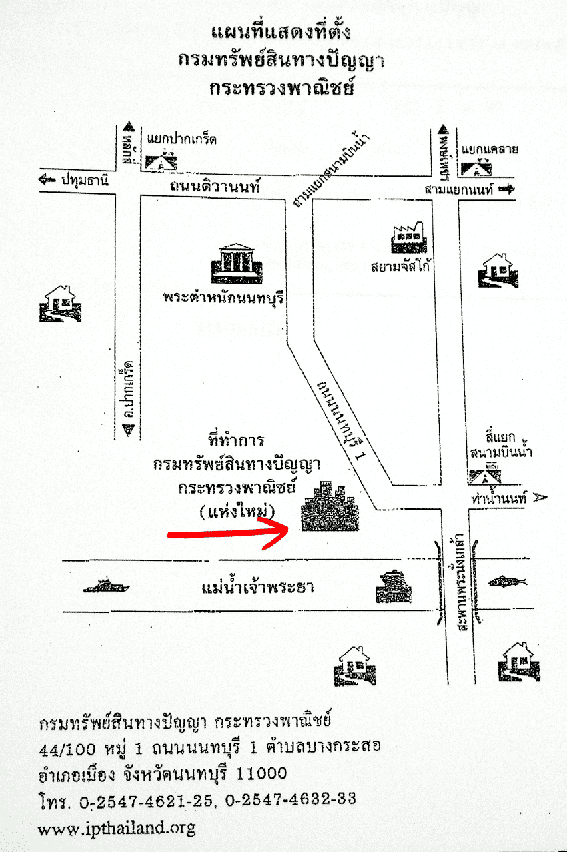
FONT Compitition
ผมจะแปะภาพแผนที่กรมทรัพย์สินทางปัญญา
สถานที่ปฐมนิเทศการประกวด font
แต่ทำไม่สำเร็จครับ
ใครสามารถกว่า
รบกวนเอาแผนที่มาแปะแทนให้ด้วยครับ
ทำไมสถาปัตยกรรมแถวๆ นั้น
ช่างดูเป็นฟอนต์ Webdings เหลือเกิน
ได้เจอตัวจริงของวงการฟ้อนต์ไทยแล้วรู้สึกตื่นเต้นมากๆ
ไว้ว่างๆอาจได้มาเล่ารายละเอียดให้อ่านถ้ามีใครอยากรู้
sketch ตัวอย่างฟอนต์ใหม่ของ DB มาด้วย
ชื่อ ดีบี จริยธรรม เข้ากับเหตุการณ์บ้านเมืองตอนนี้พอดิบพอดี
โดย คุณปริญญา โรจน์อารยานนท์
ฟอนต์ลายมือเห็น ๆ
:25: คุณปลาวาฬครับ ขอรายละเอียดงานเป็นช็อตๆ ฉากๆ แบบชัดๆ หน่อยครับ
ตูไม่ใช่คุณปลาวาฬ แต่ก็จะขอเสนอหน้าเล่าแล้วกัน
12.40 : ตูมาถึงกระทรวง เป็นอาคารที่ใหญ่ใตมาก พื้นปูด้วยหินแกรนิตอย่างดี แต่ละตึกมีเป็นสิบๆชั้น ไม่รู้ว่าโก......
12.50 : ตูมาถึงที่ลงทะเบียน จุดนั้นบรรยากาศวุ่นวายพอสมควร บางคนก็เพิ่งจะยื่นใบสมัครวันนั้นเอง (ตอนนี้หมดเขตแล้วนะ)
ส่วนคนมีตั้งแต่นิสิตนักศึกษา คนทำงาน จนถึงรุ่นคุณอาคุณลุง (มองซ้ายมองขวา รู้สึกว่าไม่มีระดับมัธยมอย่างตูเลยแฮะ)
13.00 : ตูเข้าห้อง แล้วรอโคตรนาน
13.20 : แอร์เย็นฉ่ำ ทำตูปวดเยี่ยว
13.30 : เริ่มเปิดพิธี มีการจุดธูปเทียนบูชาพระรัตนตรัย อ๊ะ ไม่ใช่... คุณศรีศักดิ์เขาก็พูดถึงจุดประสงค์-จุดมุ่งหมายในการประกวด
13.40 : มีการอบรมในเรื่อง "แบบตัวพิมพ์ไทย และความรู้เบื้องต้นฯ" โดยคุณปริญญา ผู้ออกแบบฟอนต์ดีบี
เขาจะพูดเกี่ยวกับเรื่อง ประวัติความเป็นมาของอักษรนิดหน่อย พูดถึงฟอนต์ดีบีของเขาแต่ละตัว
อย่างดีบี-ฟองน้ำ ดีบี-โซดา มีการแนะแนวทางในการออกแบบ อย่างเช่นการผสมอักษร ฟอนต์อนาโตมี
เทคนิคการหลอกตา เคิร์นนิ่ง คู่สับสน เอาง่ายๆว่าตูทั้งเปิดและปวดกบาลมากครับ
15.15 : ให้ดื่มกาแฟอันแสนขม
15.30 : อบรมในหัวข้อ"ประสบการณ์การเข้าร่วมประกวดออกแบบตัวพิมพ์" ของ อ.โรจี้ เขาก็มาพูดว่าในการประกวด
เมื่อครั้ง tepclub เป็นอย่างไรบ้าง รวมทั้งประสบการณ์อันแสนขื่นขมในยุคที่เขาใช้วิธีการวาดลงกระดาษ
เล่าประสบการณ์ว่าทำจนอ้วกมันเป็นยังไง รวมทั้งประโยคที่ผมชอบนั่นคือ "จตุพรกินหอยสังข์"
มันเอาไว้ทดสอบโครงสร้างของฟอนต์ได้ดีเลยล่ะ
16.30 : คุณประสาทอ่านข้อความในกระดาษ (ซึ่งมีอยู่แล้วในมือ) หลักใหญ่ใจความคือ
1.คุณจะต้องทำอักษรในประโยค "ศรีศักดิ์จะขอเพียงฯ" ให้เสร็จภายใน 2 สัปดาห์ต่อจากนี้
(นับเวลาตามวันที่ประทับของไปรษณีย์)
2.มีการเพิ่มรางวัล จาก 10 เป็น 13 (เลขสวยแฮะ)
- 10 ฟอนต์สำหรับตัวดิสเพลย์ที่ต้องอ่านง่าย ย้ำ ต้องอ่านง่ายแม้ขนาดเล็ก
- 2 ฟอนต์สำหรับตัวอาลักษณ์ (แต่ต้องใช้ชื่อ "ศรีศักดิ์" กับ "จามรมาน")
- 1 ฟอนต์สำหรับตัวดิสเพลย์ที่เรายินยอมให้เปลี่ยนชื่อได้ (งงมั้ย สม... ไม่อยากไปฟังเอง ช่วยไม่ได้)
3.ครั้งนี้มีผู้ร่วมประกวดทั้งสิ้นประมาณ 170 ผลงาน!!
16.50 : ให้โอกาสถาม-ตอบ ซึ่งมีอยู่ข้อนึงคือ "ฟอนต์ต้องมีหัว แต่ไม่จำเป็นว่าต้องหัวกลวง" อันนี้ไปตีความกันเอาเอง
17.00 : ตูกลับบ้านทางเรือ จากท่าน้ำนนท์ไปสี่พระยา ถึงบ้าน 2 ทุ่ม อิ่มเอมครับ